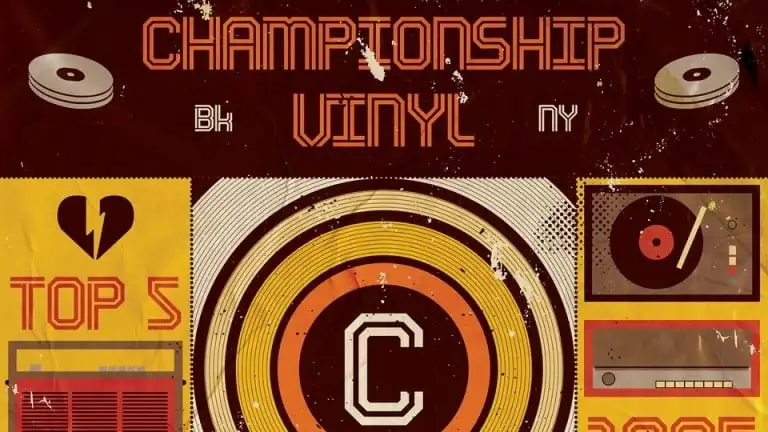
A Wim Pro Display é uma fonte inspirada nos estilos de letras esportivas. Desenhada por Rafael Nascimento na plataforma 99designs, ela adere-se aos elementos dos adesivos tipográficos do começo dos anos setenta e a obra inspiradora de Wim Crouwel. Esta fonte é concebida para uso em displays ou elementos visuais mais destacados, oferecendo uma aparência futurista que combina com estilos clássicos. A nova versão da Wim Pro Display apresenta menos características mecânicas e inclui um conjunto de ligaturas – 637 relacionadas a letras e outra série composta por 57 ligações para números. Com sua rica história inspiradora, esta fonte é perfeita para designers buscando elementos visuais que unem tradição e modernidade, transformando qualquer projeto em um visual de alta qualidade.